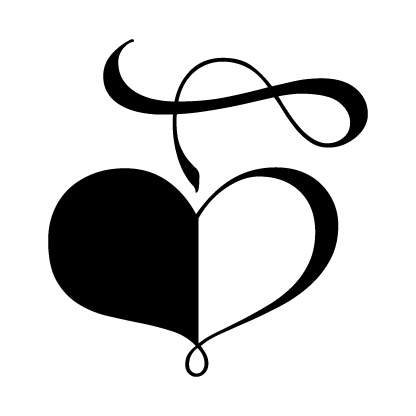
Les vignette ci-dessous ont été dessinées par Hermann Zapf pour le Zapfino. Pour y accéder il faut ouvrir la fenêtre des Glyphes dans InDesign d’Adobe. Zapf a dessiné ces vignettes, il avait déjà quelques 80 ans. La main toujours aussi sûre. Et plein d’humour.